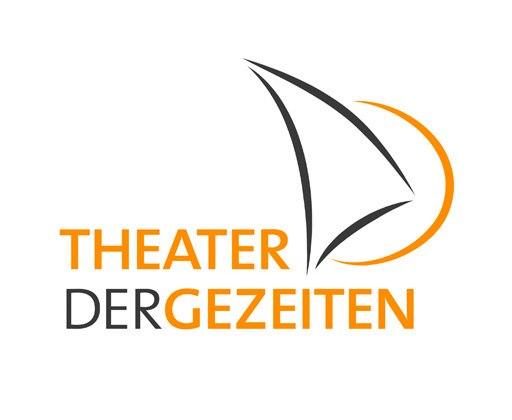
Schriftart aus dem Logo des Theater der Gezeiten (Bochum) gesucht
Da die ursprüngliche Vorlage für das Logo nicht mehr vorhanden ist, bräuchten wir für die Reproduktion des Logos einen Hinweis auf die verwendete Schriftart. Eine erste Suche führte zur Antique Olive,  allerdings passt hier die Breite einiger Buchstaben (G, Z, N) nicht.
The Sans.